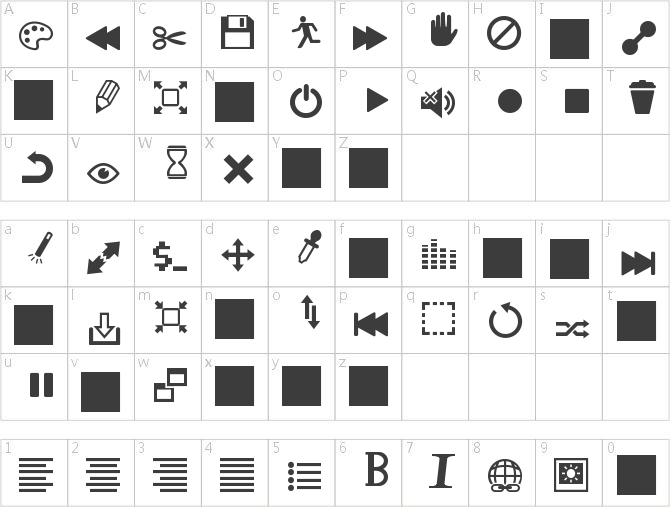
Heydings Controls 詳情頁(yè)
Heydings Controls字體字庫(kù)是一款讓人賞心悅目、百看不厭的英文字體,適合各類廣告和產(chǎn)品包裝設(shè)計(jì)應(yīng)用,字體大小0.01MB,格式為ttf字體,上傳用戶是文生電腦,作者/版權(quán)方為未知